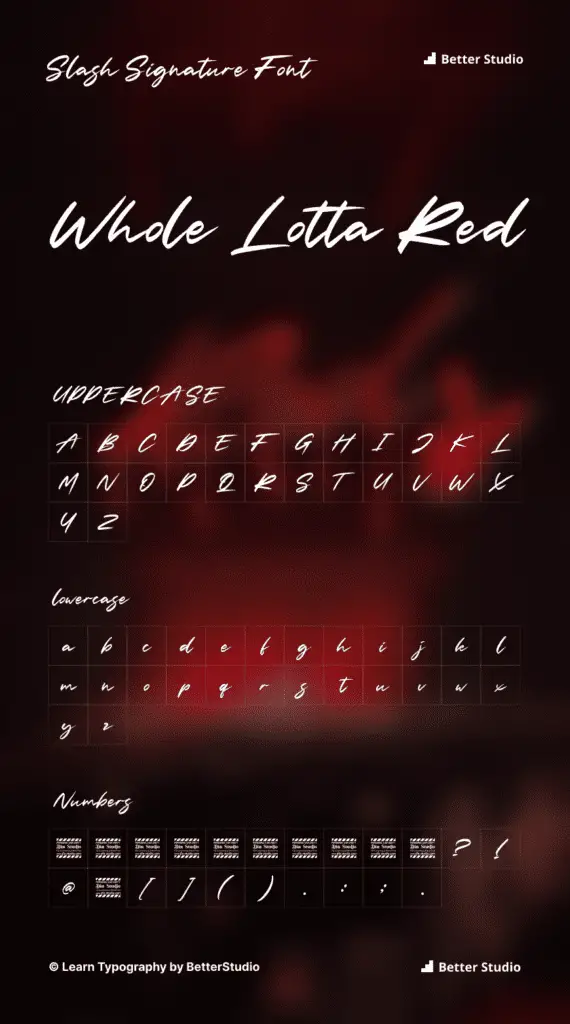
Whole Lotta 红色字体
已发表: 2023-03-28毫无疑问,自 2021 年首次亮相以来,Whole Lotta Red 已成为电影海报和其他营销材料的流行字体。
除了您将在 3d Studio 中找到的经典无衬线字体外,您还会发现各种现代变体,它们肯定会吸引全世界平面设计师的注意力,因为他们每天都在寻找灵感。
你会注意到 Din Studio 字体是经典无衬线字体与现代风格的结合,一定会引起全世界平面设计师的注意。
由于其受欢迎程度,Whole Lotta Red 已成为当今设计行业中最受欢迎的字体之一。
Whole Lotta Red 使用哪种字体?
我们能找到的与我们发现的 Whole Lotta Red 海报中使用的字体最接近的字体是Slash Signature 。
尽管我们尽最大努力找到 Whole Lotta Red 海报中使用的确切字体,但我们无法找到它; 因此,我们假设字体已经过定制以满足品牌的需求。
但是,此处使用的字体与我们发现的另一种设计相似的免费字体非常相似。 它名为 Slash Signature,由 Din Studio 设计。 这种字体很相似,但它是一种免费字体。
Whole Lotta 红色字体
Slash Signature 的替代品和类似样式
下面列出了五种可以在设计和使用方面替代 Slash Signature 的替代字体,以及它们的相似性:
- 打开 Sans 字体
- 拉托字体
- Helvetica Neue 字体
- 机器人字体
- 蒙特塞拉特字体
谁设计了 Whole Lotta 红色字体?
当您需要时,Whole Lotta Red 字体系列就会出现。 该字体由Din Studio设计,这是一家位于加利福尼亚州旧金山的小型设计公司。
Din Studio 成立于 2012 年,并迅速成为整个排版行业中最成功和最知名的品牌之一。
他们独特的风格帮助他们找到现代和传统字体之间的完美平衡,这是他们的专业领域之一。
该公司与业内一些知名企业合作,为耐克、苹果和谷歌等享誉全球的公司创建定制字体。
Whole Lotta Red 字体背后的首席设计师是 John Smith。 约翰在平面设计领域已有超过 15 年的经验,他的经验和技能使他成为 Din Studio 成功的重要组成部分。
他非常小心地确保他设计的每一种字体在呈现时都感觉恰到好处,因为他对排版充满热情,并且在他的所有作品中都闪耀着光芒。
Whole Lotta Red:简要概述
作为 2017 年恐怖电影“It”的电影海报设计的一部分,由 Andy Muschietti 执导,使用 Whole Lotta Red 五彩纸屑创建了多种字体。
它的设计完美地衬托了影片标志性的红色气球和令人毛骨悚然的小丑形象。
字体有一些非常大胆和棱角分明的东西,其特点是锐角和尖锐的衬线,给人以力量和危险的整体印象,因此,使它成为恐怖电影海报上使用的完美字体,因为它给人一种字体的力量感
此外,该字体还融入了 Whole Lotta Red 标志的标志性斜杠,其标志性的形状随着时间的推移已成为该品牌的代名词。
在许多角色中,斜杠出现在他们名字的末尾,以赋予他们独特而引人注目的外观。 这条斜杠现在已经成为电影品牌不可或缺的一部分,在与电影相关的其他类型的媒体中也经常看到。
包起来
除了令人印象深刻的强大和适应性之外,Whole Lotta Red 已迅速成为各种项目的热门选择,从电影海报和书籍封面到广告活动和徽标设计。
无论是什么,无论您是想创造一些险恶的还是更乐观的东西,Whole Lotta Red 字体都一定会让您的项目脱颖而出,无论您选择将其用于什么目的。